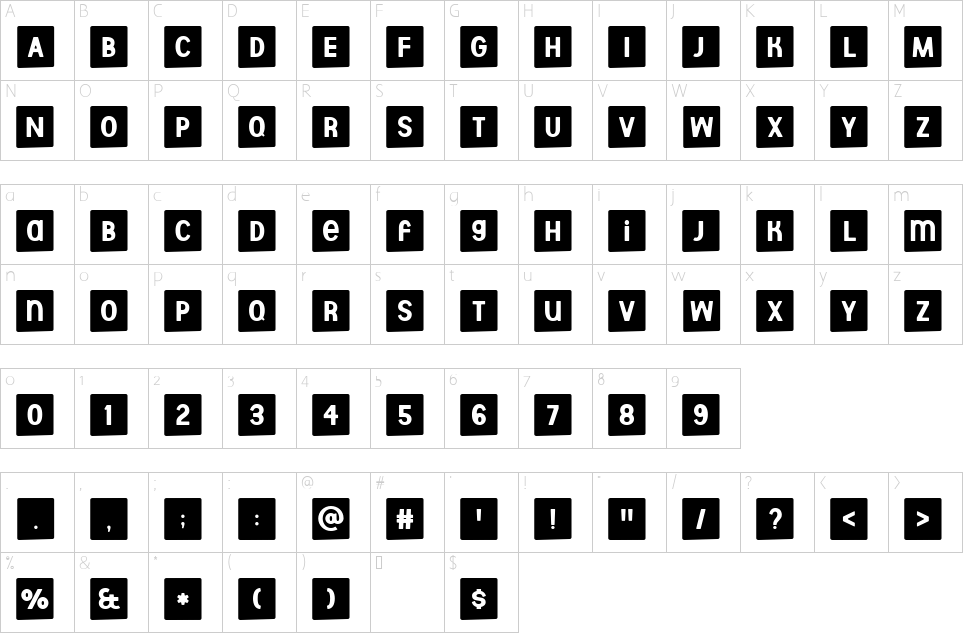
Aberforth Tiles é uma fonte de estilo único que se destaca em páginas gráficas com suas bordas suaves e texturas de azulejos. Desenhada por Brittney Murphy, esta fonte foi projetada para fornecer uma textura que pode ser usada em diversos contextos, desde designs de interiores até ilustrações de arte digital. Com uma versão disponível tanto para Windows quanto para Mac, Aberforth Tiles oferece aos designers a oportunidade de incorporar um toque especial em seus trabalhos. Desenvolvida por Brittney Murphy, a fonte já foi baixada 12,814 vezes, indicando a sua popularidade entre designers e criadores de conteúdo digitais. A Aberforth Tiles é uma escolha inteligente para quem busca uma fonte de estilo único, versátil e fácil de usar.